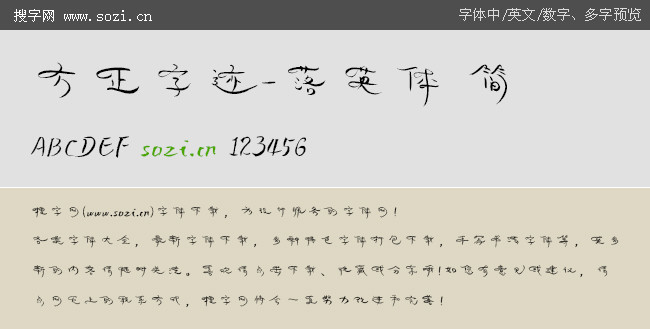
方正字跡-落英體簡
搜字網(wǎng)提供一款方正字跡-落英體簡中文字體下載,每一個字都是一株生長的藤蔓。每一筆延伸的筆畫,都是一支窈窕的枝丫;每一處轉(zhuǎn)彎的圈圓,都是一片飄落的花瓣。作者的設(shè)計靈感來源于隸書,又融入了個人的書寫風(fēng)格,一步步從隨手記的字體發(fā)展至今。給人傳遞一種愜意、自如而又美好的感覺。